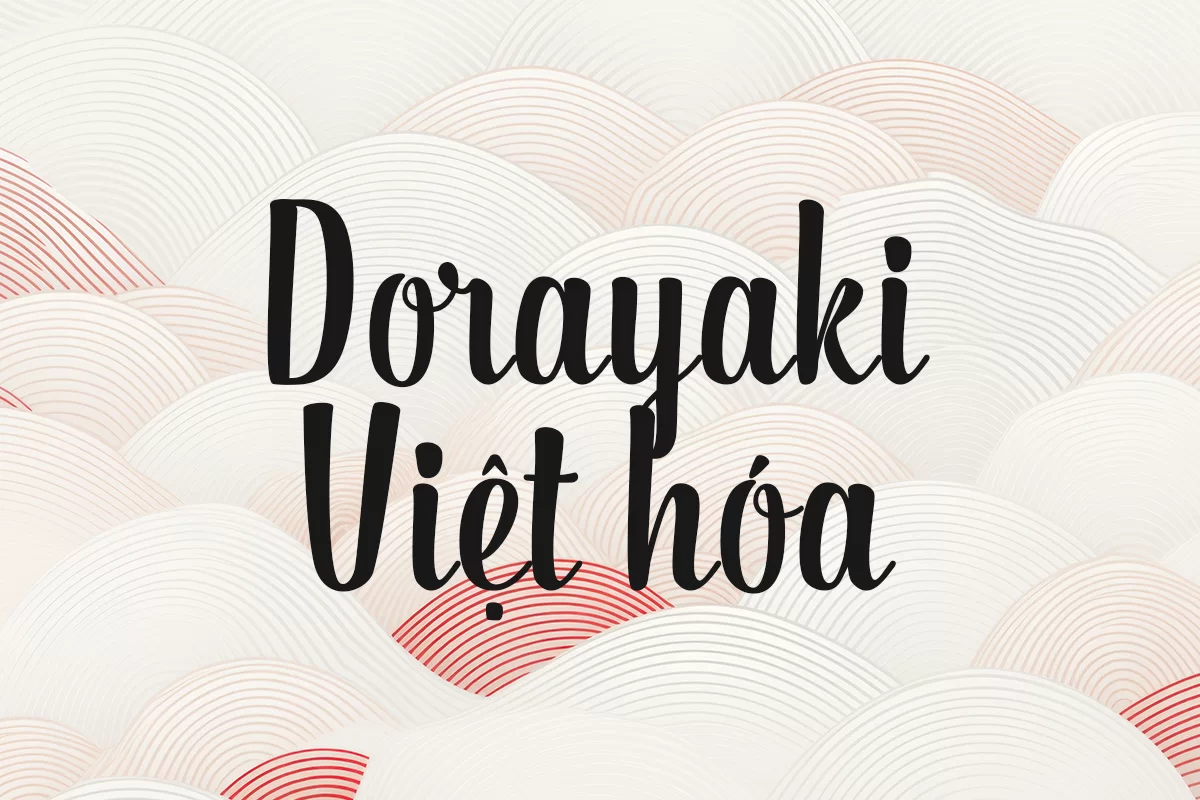
Font Dorayaki Việt hóa mang đến cảm giác ngọt ngào và thân thiện với nét chữ mềm mại, tròn trịa như chính tên gọi của nó – một món bánh truyền thống Nhật Bản. Với phong cách script pha lẫn sans-serif, Dorayaki không quá cầu kỳ nhưng vẫn đủ tinh tế để tạo ấn tượng thị giác. Các nét nối uyển chuyển giữa các chữ cái, đặc biệt là phần đuôi cong nhẹ ở chữ “y”, “k” hay các dấu diacritics (dấu tiếng Việt) được Việt hóa khéo léo, giúp font giữ nguyên sự đồng bộ thẩm mỹ.
Phù hợp với các thiết kế bao bì, tiêu đề poster, thiệp mời cưới, hoặc các dự án mang tính nữ tính, nhẹ nhàng và thân thiện. Dorayaki không chỉ là một font chữ, mà còn là một “vị ngọt thị giác” làm tăng cảm xúc trong từng thiết kế.